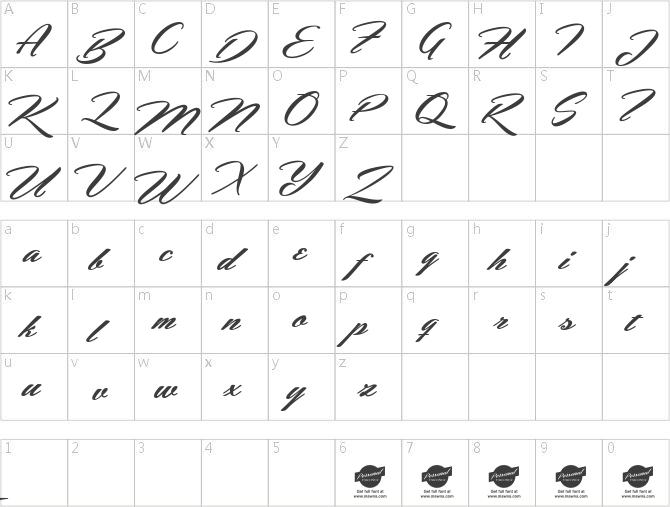
字体名称: Hemmet_
Hemmet_Personal_Use_Only
Hemmet_Personal_Use_Only介绍
Hemmet_Personal_Use_Only字体字库是一款让人赏心悦目、百看不厌的英文字体,适合各类广告和产品包装设计应用,字体大小0.17MB,格式为ttf字体,上传用户是小李哥/,作者/版权方为未知